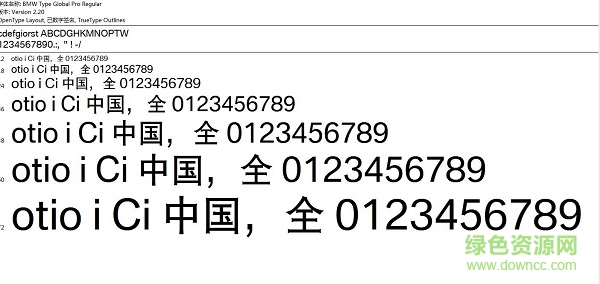
bmw type global pro regular
bmw type global pro regular字體是一款常見的寶馬廣告字體,結(jié)構(gòu)均勻,風(fēng)格獨(dú)特,整體設(shè)計(jì)精致,給人的印象是舒服而亮眼,有需要者快來本站下載吧!
bmw type global pro regular